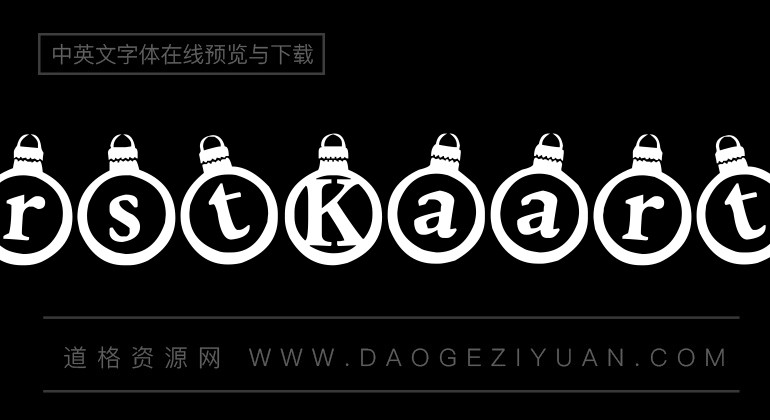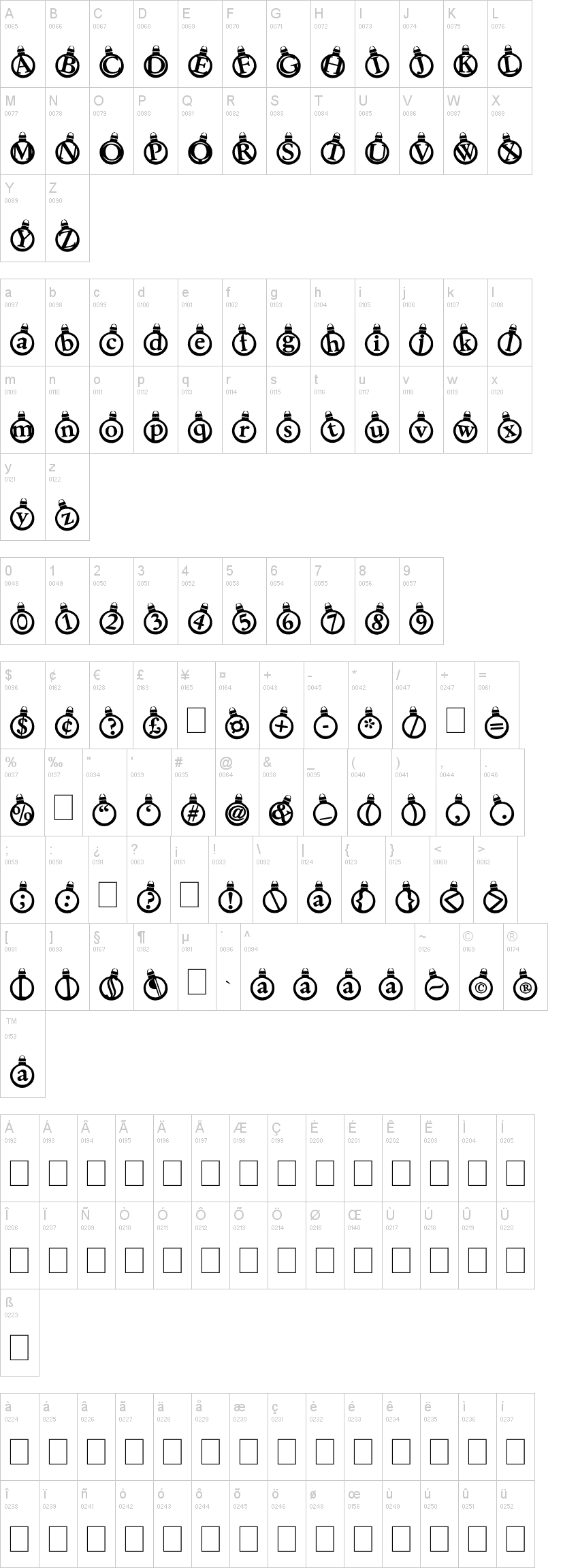
KerstKaarten
KerstKaarten 字体是一款具有欧洲风格的节日贺卡字体,由荷兰设计师克里斯·拉夫特(Chris Laft)设计。它是一种经典的节日字体,以古老的欧洲风格和精致的细节设计而闻名。它具有温暖的色彩,可以用于制作节日贺卡、海报、宣传单等,为节日添加浪漫的气氛。
KerstKaarten是一款非常不错的手写艺术字体,具有很好的视觉感,适合于文化类的宣传设计、商业类品牌的广告和产品包装设计以及个性化文字排版等较多场景。